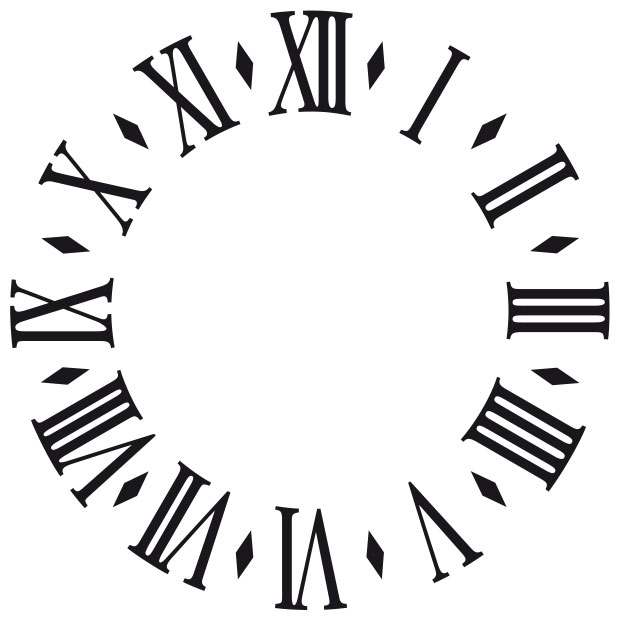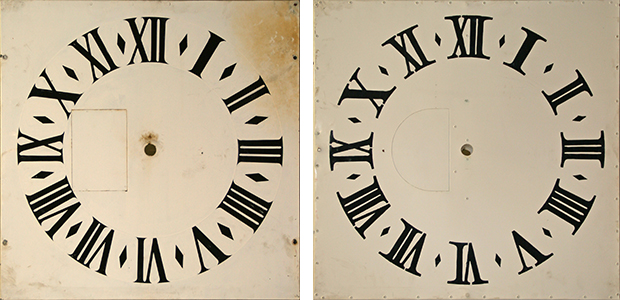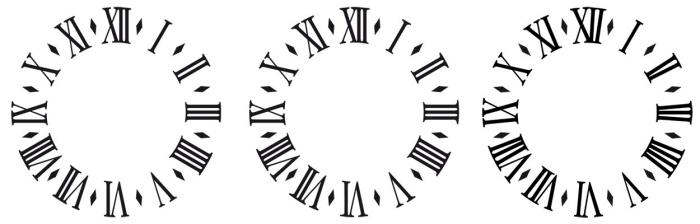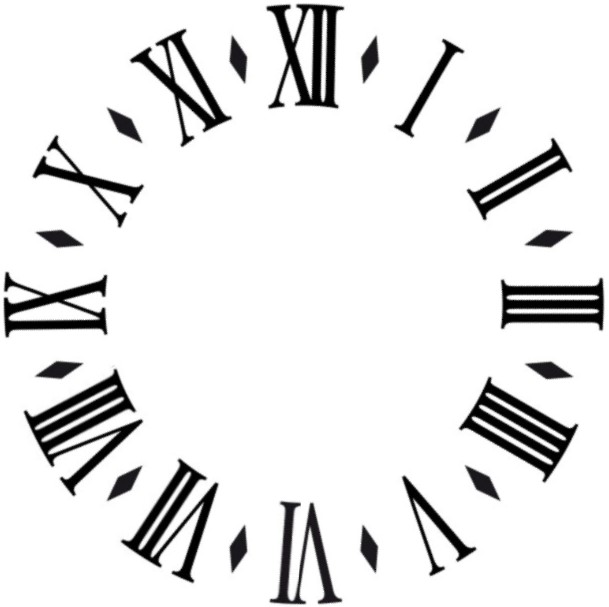
Schmallaufende römische Ziffern
In die Kirche hat der Biltz eingeschlagen.
Nun sollen, wo doch das Gerüst steht, die Ziffernblätter der Turmuhr neu lackiert werden.
1) Ich möchte die handgemalten Ziffern möglichst nachahmen, dazu benötige ich eine sehr englaufend Schrift, denn der Platz für die Ziffern ist begrenzt. Ich finde jedoch keine und bin für einen Tipp dankbar.
2) Wahrscheinlich aus Platzmangel hat der Maler die 1 (also I) wesentlich breiter gezeichnet als bei II, III und IIII, das gleiche gilt für X und XI usw. Ist das bei Ziffernblättern üblich? Mich stört es schon.
Dass man die 4 in Form von IIII darstellt anstat von IV, kommt bei Ziffernblättern wohl häufig vor. Mir war das neu.
Eines der vier Blätter wurde wohl zu späterem Zeitpunkt nachgemalt. Es zeigt deutlich andere Schriftformen.
Muß man das denn mit einer Satzschrift machen? Kann man nicht die Originalformen nachzeichnen (analog oder am Rechner, das ist erst einmal nachrangig) und nur kleinere Fehler glätten (die I würde mich auch in den Wahnsinn treiben).
Ansonsten: Eine sehr schmal laufende Klassizistische wäre die
Wahrscheinlich aus Platzmangel hat der Maler die 1 (also I) wesentlich breiter gezeichnet als bei II, III und IIII, das gleiche gilt für X und XI usw.
Wenn die I aus Platzmangel anders gezeichnet worden wäre, dann hätte man sie aber doch eher schmaler und nicht breiter machen müssen. Es ist wohl eher so, dass man die Zahlen je nach Platzbedarf mal schmaler und mal breiter gemacht und dabei auch die Strichstärken »angepasst« hat (siehe zum Beispiel die X in IX und X).
Oder es hat mit dem Betrachtungsabstand zu tun. So ein Ziffernblatt hängt doch ziemlich weit oben. Eventuell wirkt ein normales I aus der Entfernung betrachtet zu dünn.
Aber grundsätzlich würde auch ich versuchen das Original nachzuzeichnen.
Die 5 (V) und die 10 (X) sind auch dicker. Mir scheint, überall da, wo die Zahlen nur aus ein oder zwei Strichen gebildet werden, wurde dieses »Defizit« durch eine großzügigere Strichstärke ausgeglichen.
Zuerst hatte ich überlegt, ob die Uhrzeiten mit den dicken Zahlen eine bestimmte Bedeutung hatten, aber traditionell waren das auf dem Land eher 6, 9, 12 und 18 Uhr, die die Zeiten für Arbeitsbeginn, Pausen und Feierabend angaben und durch ausdauerndes Läuten markiert wurden – sofern mich meine Erinnerung da nicht trügt.
Es ist wohl eher so, dass man die Zahlen je nach Platzbedarf mal schmaler und mal breiter gemacht und dabei auch die Strichstärken »angepasst« hat (siehe zum Beispiel die X in IX und X).
Die 5 (V) und die 10 (X) sind auch dicker. Mir scheint, überall da, wo die Zahlen nur aus ein oder zwei Strichen gebildet werden, wurde dieses »Defizit« durch eine großzügigere Strichstärke ausgeglichen.
Ja klar, die unterschiedlichen Breiten und Strichstärken sind durch den Versuch entstanden, das unterschiedliche optische Gewicht der Zahlen etwas anzugleichen. Das ist natürlich sehr laienhaft gemacht worden und dabei auch mehr Schaden als Nutzen angerichtet. Trotzdem kann man das denkmalgerecht sanieren, indem man die unsterilen, händischen Formen aufgreift, aber die schlimmsten Verwerfungen überbügelt.
Ich hatte gehofft, es gäbe eine schmal laufende Klassizistische, die mit den Serifen einigermaßen passen würde. Es wäre deutlich weniger Arbeit als das Nachzeichnen und Fehler beseitigen. Es muss digital sein, weil ich für den Malermeister eine Kaschierfolie (eine Schablone als Klebefolie) anfertigen soll. Grundsätzich sehe ich auch in dem Händischen und Unglatten einen Wert. Aber das Ding hängt nun mal am Turm, und von unten sieht man nicht ob das moderne Satzschrift oder Handarbeit ist, wenn es denn eine passende Satzschrift gäbe.
Also ran an die Arbeit, eigentlich sind es ja nur drei Buchstaben! Wenn ich mich traue, zeige ich das Ergebnis.
Ich hatte gehofft, es gäbe eine schmal laufende Klassizistische, die mit den Serifen einigermaßen passen würde.
Neben der oben verlinkten Onyx fällt mir noch die Century condensed ein, auf die man vielleicht aufbauen könnte:
Danke Pachulke, ich habe auch noch eine gefunden:
So hab’ ich das Zifferblatt gebastelt:
1) Ziffern gezeichnet in Anlehnung an die an die Coporate A Condensed, die ich dann doch noch fand.
2) Sehr enge Ligaturen gebastelt
3) Ziffern im Kreis platziert
4) Und jetzt kommt’s: Die einzelnen Serifen in die Außen- und Innenrundung gebracht. Bei der 1 (I) ist das kein Problem, aber bei den breiten und unsymmetrischen Buchstaben mussten die Serifen ganz schön weit verschoben werden.
5) Jeden vertikalen Strich der Serifen habe ich dann aufs Zentrum hin ausgerichtet, also an einer Geraden durch den Mittelpunkt. Somit steht die Serife im rechten Winkel auf der Rundung und gibt es keine Serife zweimal.
Außerdem stellt sich die Frage, inwiefern man mit der Schrift auch die Gesamtkontur des Ziffernblattes verzerren müßte, die dann nicht mehr rund / quadratisch, sondern ellyptisch / trapezförmig wäre.
Je mehr ich darüber nachdenke, desto weniger denke ich, daß das jemand macht. Das Gehirn rechnet die Verzerrung gewohnheitsmäßig raus, das muß ja ohnehin auch die seitliche Verzerrung bei seitlichem Betrachtungswinkel weginterpolieren, da kommt es auf die Höhenverzerrung auch nicht mehr an.